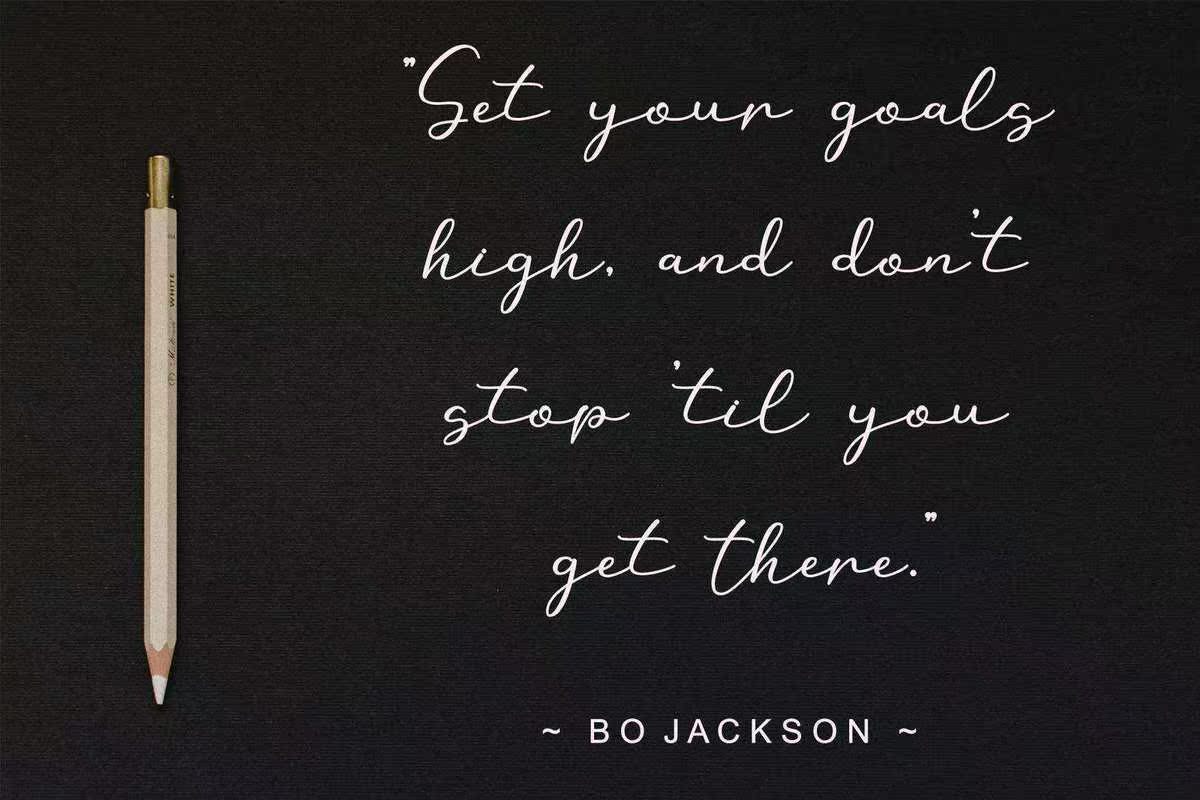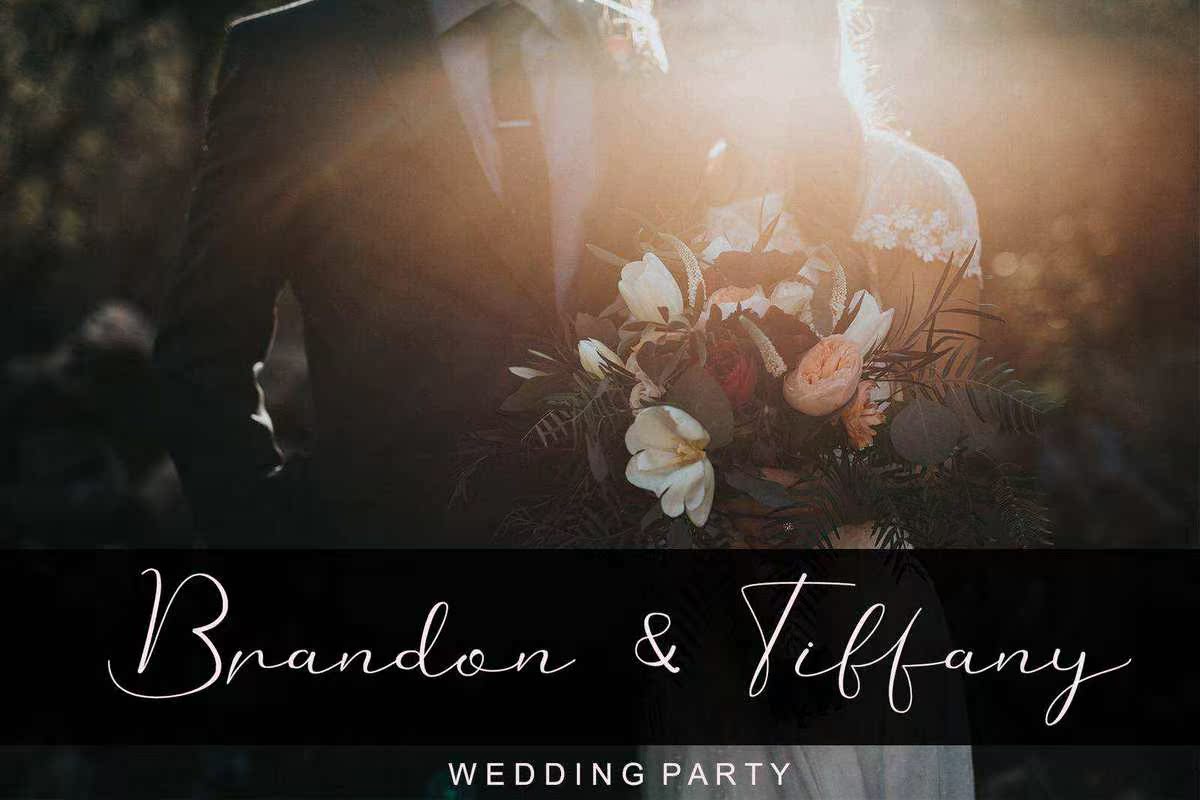
GeollittaFontIsofmanyFontByletteRafa.It是一个流动的字母,它将使您的设计和周末看起来更完美;欢迎卡、包装设计、耐磨性、工艺设计、任何DIY项目、书名、婚礼宣传、包装等。GeollitaFontIsoneofmanyFontByletter Rafa。其流动字母将使您的设计更具吸引力和周感。GeollitaFontIsPerfect;贺卡、包装设计、耐磨性、工艺设计、任何项目、书名、婚礼宣传、包装等等。